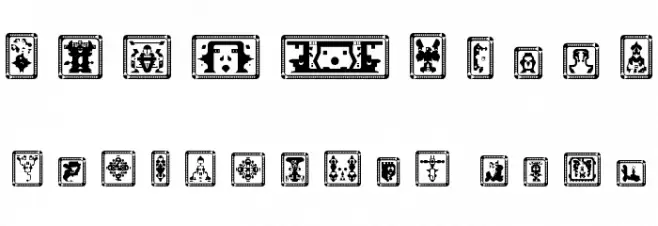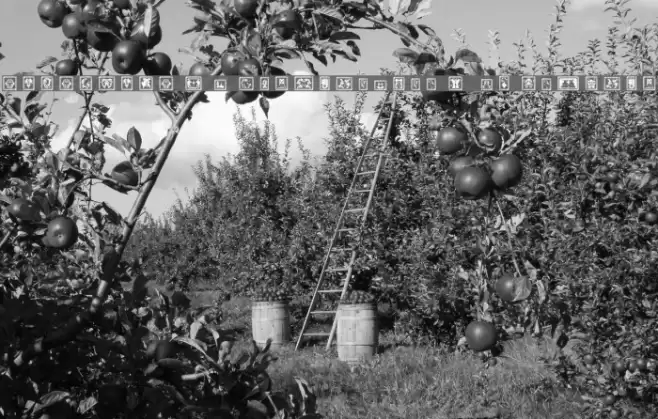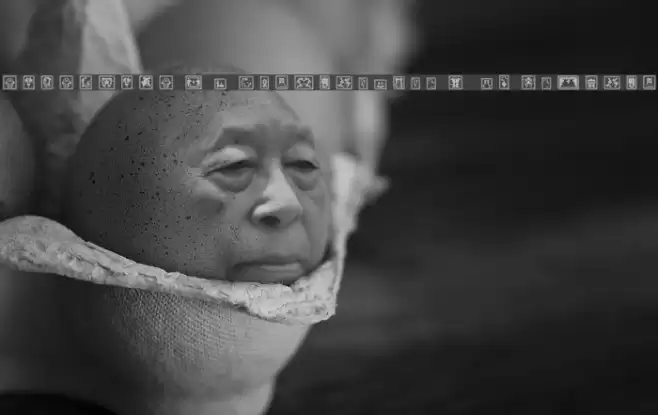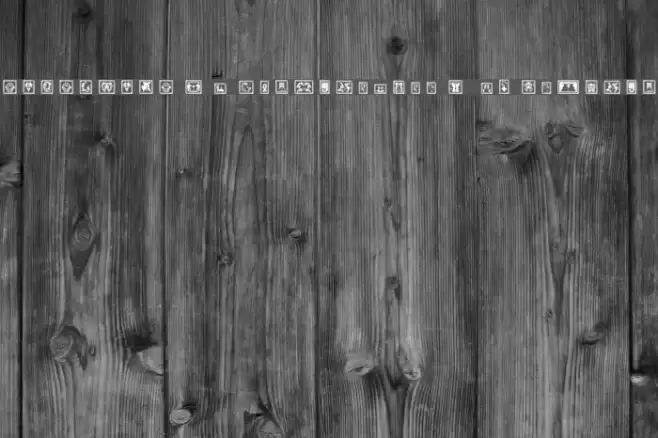
TESTAMENT B / Formaldhyde 1 à 80 Regular Font
✎ Dingbats
| Kategorien | Dingbats |
| Anwendungsfall | Logos, Headlines, Artistic Projects |
| Vorgeschlagene Projekte | Ideal for creative projects such as posters, album covers, or artistic branding where a unique and eye-catching font is needed. |